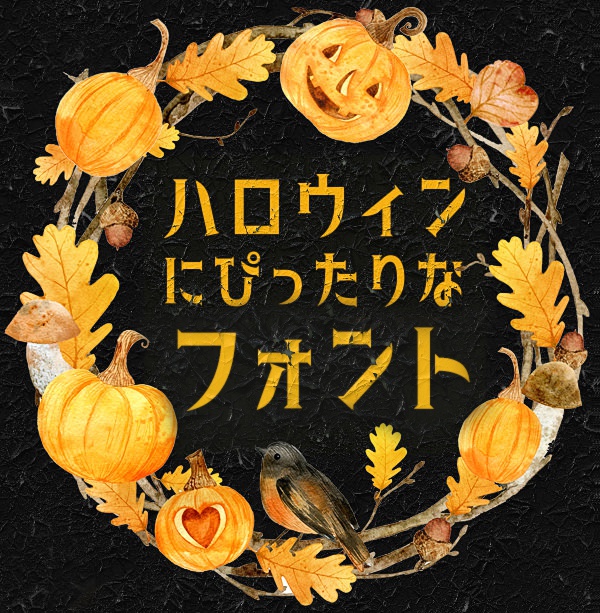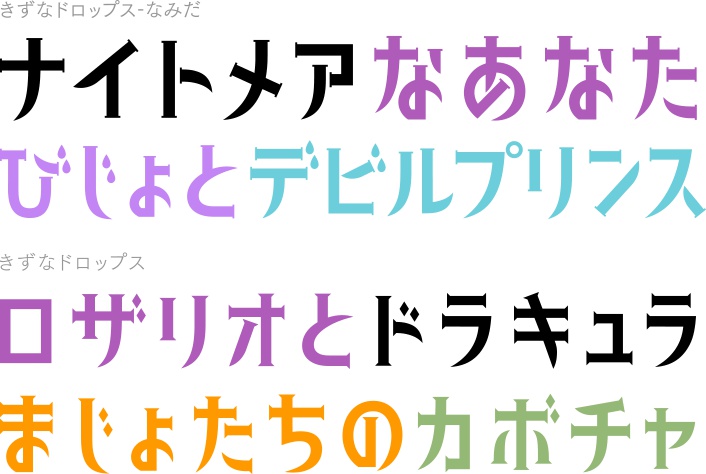
きずなドロップス フォント
静寂の時を表現するような緊張感のあるフォントをと思い制作しました。先端のセリフの形状が印象的な、宝石のようなキラキラ感のある書体です。 縦長(長体)ぎみの可憐なデザインは女性らしい凜とした雰囲気にもピッタリです。ハロウィンやクリスマスなどの季節のイベントにも大活躍すると思います。先端と濁点のデザインが、より乙女チックな印象の「きずなドロップス-なみだ」も収録されています。こちらは濁点の形状は水滴型になっておりユニークかつキャッチーな魅力に溢れています。 動作環境 Mac:システム/OS X対応(10.x)〜最新のOS X Windows:OS/日本語版Windows2000、XP、VISTA、Windows7〜11以降 フォント形式:OpenTypeフォント 収録文字数について ひらがな、カタカナのみの書体になります。 安心して使えるロイヤリティフリーの書体 あらゆる商用・デザイン用途(印刷物・ゲーム・アプリ・映像・動画・ロゴ・同人作品)に使用できる、商用申請の必要のないロイヤリティフリーの書体になります。文字の加工・変形も可能です。ご安心ください。